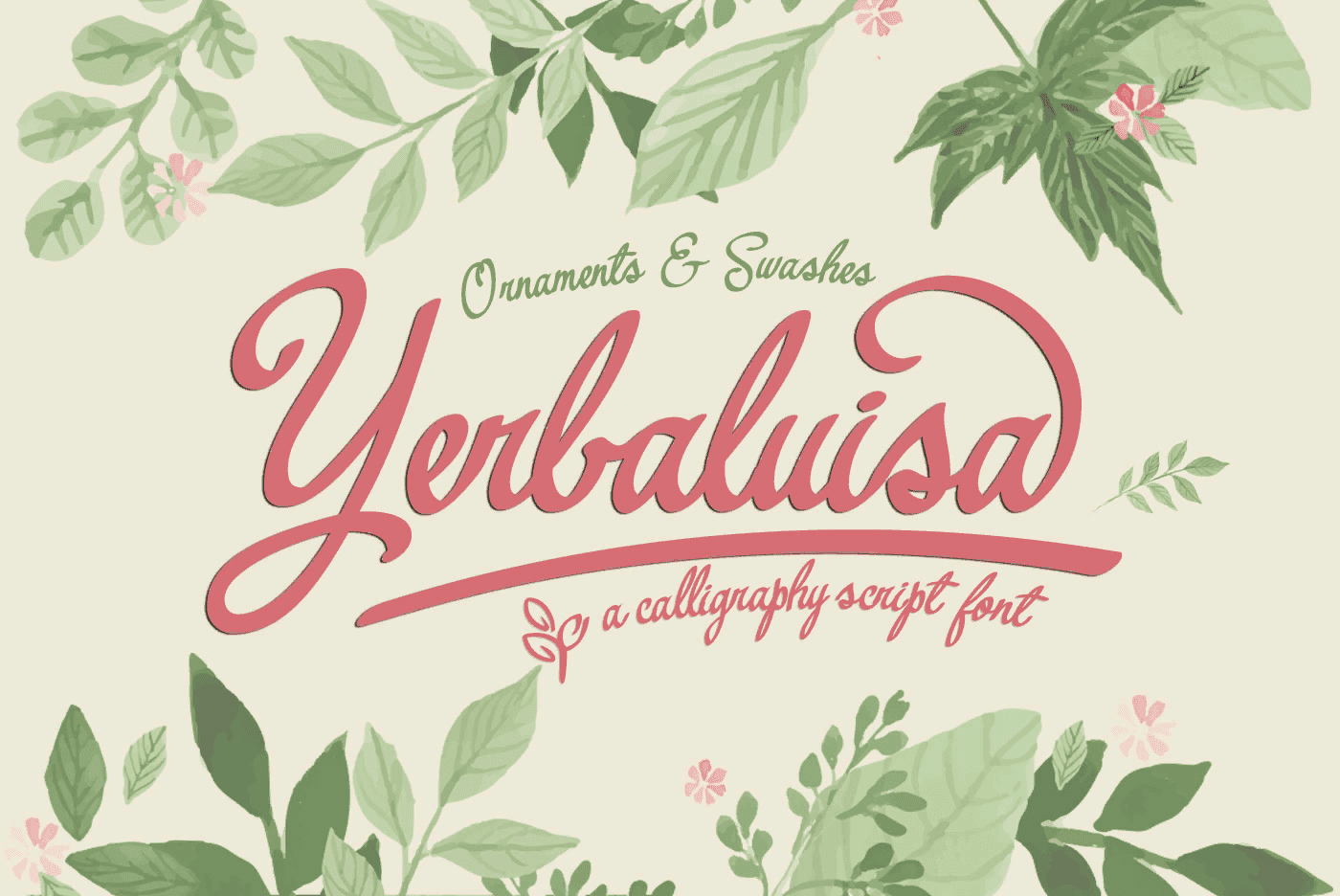
Название: Yerbaluisa Font (2021)
Yerbaluisa - это рукописный каллиграфический стиль шрифта с конкатенированными буквами и несколькими наборами орнаментов и штрихов.
Название: Yerbaluisa Font (2021)
Yerbaluisa - это рукописный каллиграфический стиль шрифта с конкатенированными буквами и несколькими наборами орнаментов и штрихов.